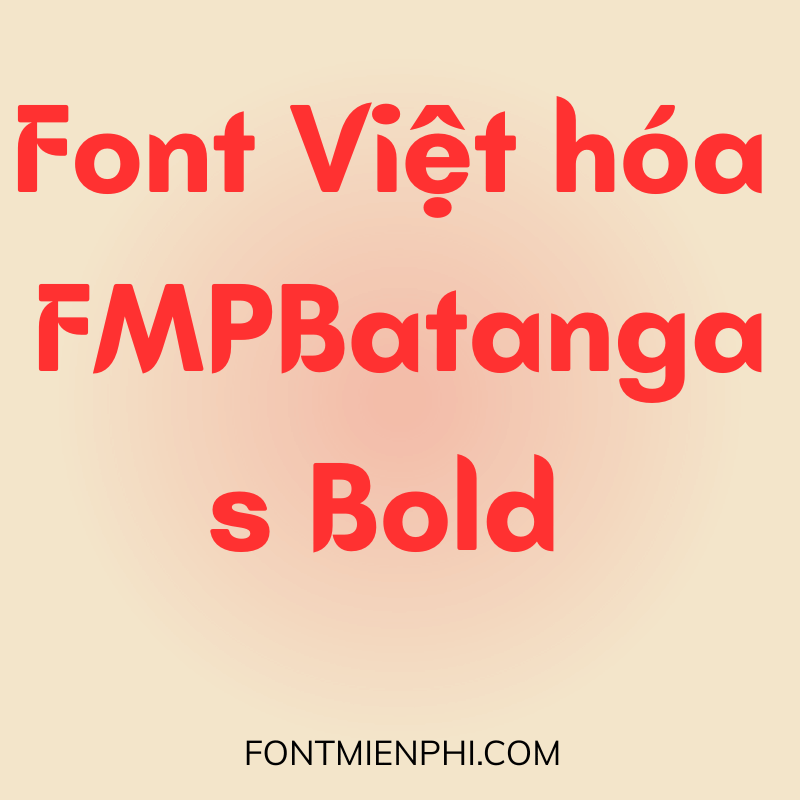
Font Việt hóa FMP Batangas Bold
Giới thiệu về Font Việt hóa FMP Batangas Bold
Trong thế giới đồ họa hiện đại, việc lựa chọn một bộ Font Miễn Phí chất lượng là yếu tố then chốt để tạo nên sự khác biệt. Font Việt hóa FMP Batangas Bold nổi lên như một lựa chọn hàng đầu cho các nhà thiết kế đang tìm kiếm sự mạnh mẽ và cá tính. Đây là phiên bản được tinh chỉnh kỹ lưỡng, hỗ trợ đầy đủ bộ gõ tiếng Việt, giúp bạn loại bỏ hoàn toàn nỗi lo lỗi font khi làm việc trên các phần mềm chuyên dụng như Photoshop hay Illustrator.
Đặc điểm thiết kế nổi bật
Đúng như tên gọi, Font Việt hóa FMP Batangas Bold sở hữu những nét vẽ dày, chắc chắn và đầy uy lực. Các góc cạnh được cắt gọt tinh tế, mang lại cảm giác hiện đại nhưng vẫn giữ được sự trang trọng cần thiết. Kiểu chữ này cực kỳ phù hợp cho các tiêu đề lớn, banner quảng cáo hoặc logo thương hiệu cần sự khẳng định mạnh mẽ. Với độ tương phản cao, font chữ này đảm bảo khả năng hiển thị tốt trên cả nền tảng in ấn lẫn kỹ thuật số.
Ứng dụng của Font Việt hóa FMP Batangas Bold trong thực tế
Bộ font này không chỉ giới hạn trong thiết kế chuyên nghiệp mà còn rất hữu ích cho học sinh và giáo viên trong việc làm slide bài giảng hoặc báo cáo. Sự rõ ràng của từng ký tự giúp người xem dễ dàng tiếp nhận thông tin từ xa. Ngoài ra, các bạn trẻ có thể sử dụng font để thiết kế áo lớp, thiệp mời hoặc các ấn phẩm truyền thông mạng xã hội đầy sáng tạo.
Lưu ý khi sử dụng
Dù có thiết kế ấn tượng, bạn nên kết hợp Font Việt hóa FMP Batangas Bold với các font chữ không chân (sans-serif) mảnh hơn để tạo sự cân bằng cho thị giác. Tránh sử dụng font đậm này cho các đoạn văn dài vì có thể gây mỏi mắt cho người đọc.